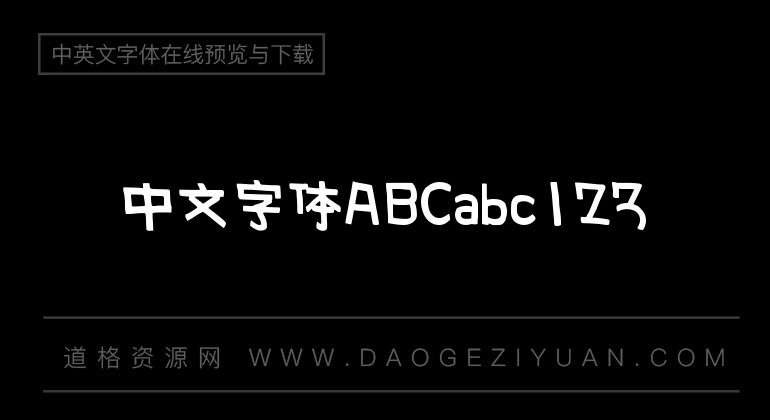
Aa字体管家手写海报体
Aa字体管家手写海报体是一种手写风格的中文字体,适用于海报、广告、书籍封面等设计领域。它具有极具个性化、独特的笔画风格,每一个笔画都显得非常生动和自然,犹如真实的手写字体。此字体的笔画线条流畅,整体呈现出一种轻松自由的感觉,同时,也保留了传统汉字的特色,让人感觉古朴而有文化气息。此外,Aa字体管家手写海报体字体包含了常见的汉字、标点符号等,方便了设计师的使用。
Aa字体管家手写海报体是一款非常不错的手写艺术字体,具有很好的视觉感,适合于文化类的宣传设计、商业类品牌的广告和产品包装设计以及个性化文字排版等较多场景。